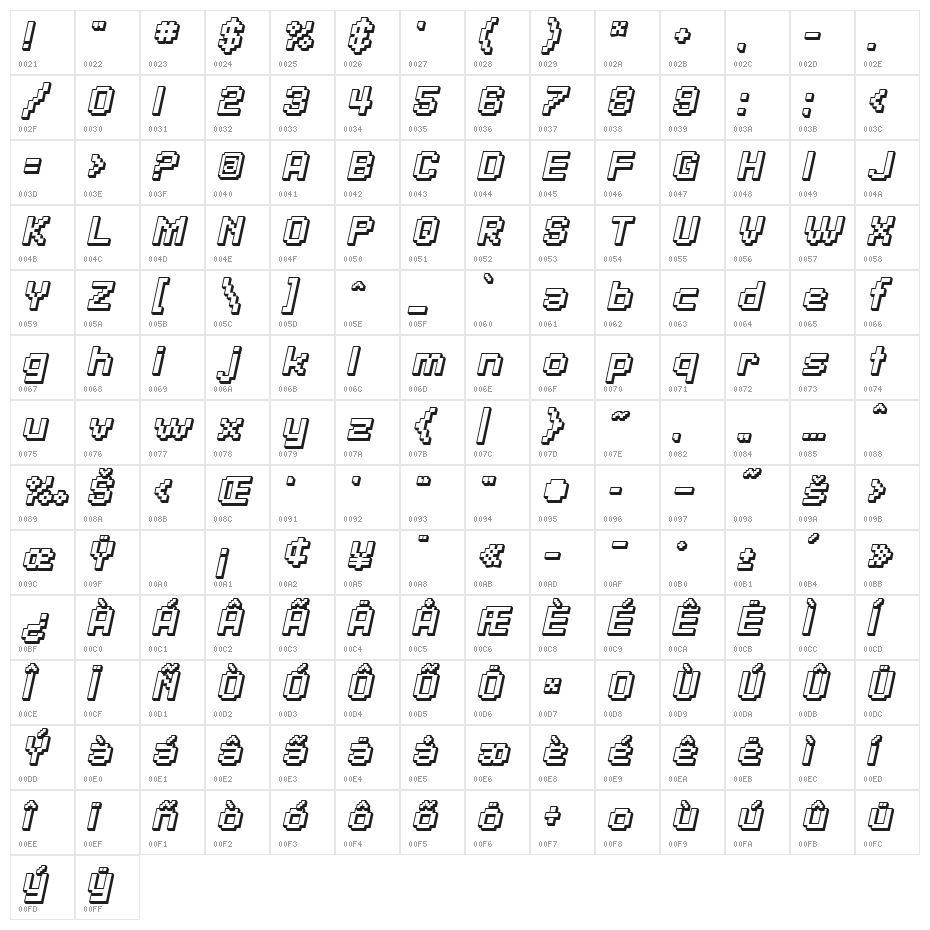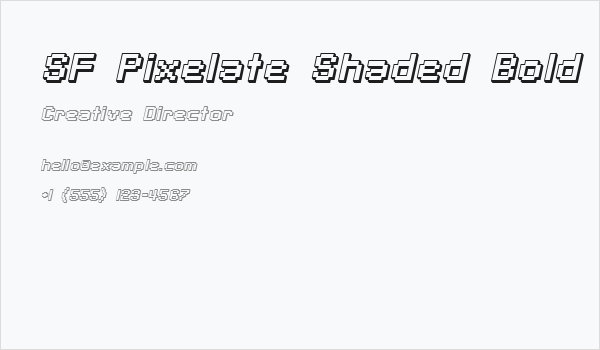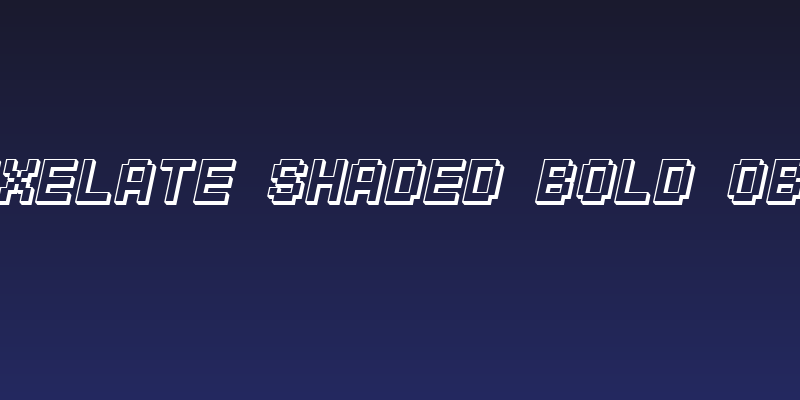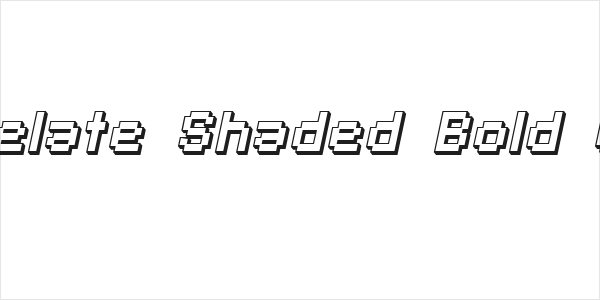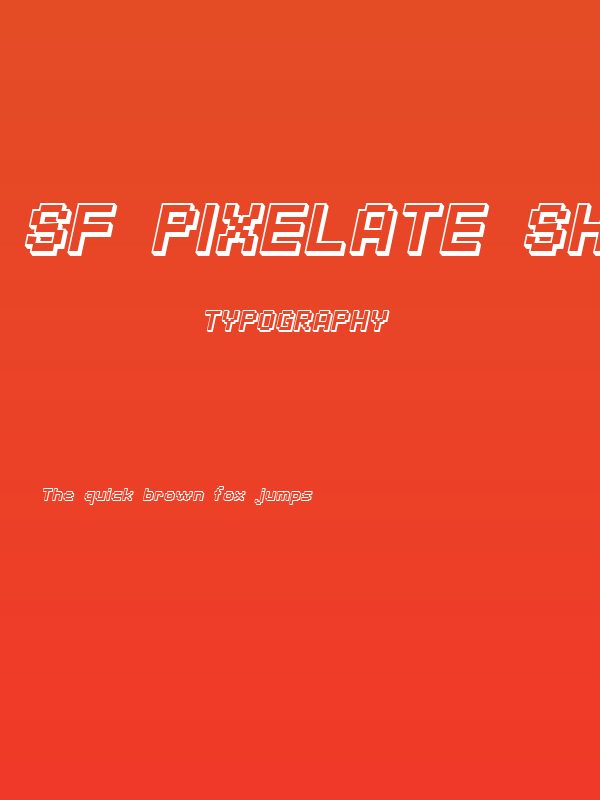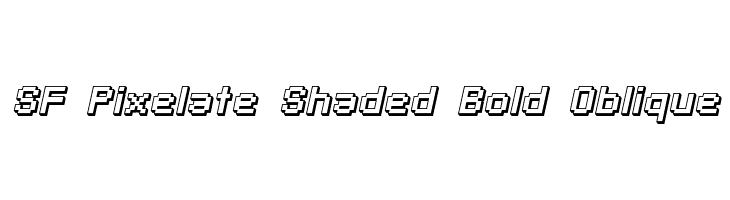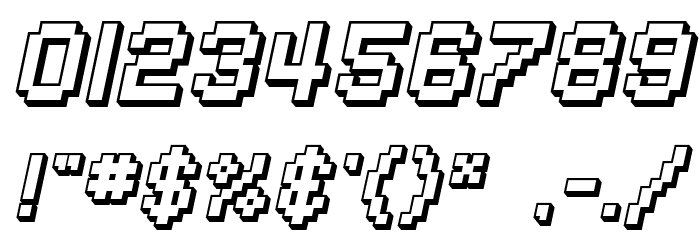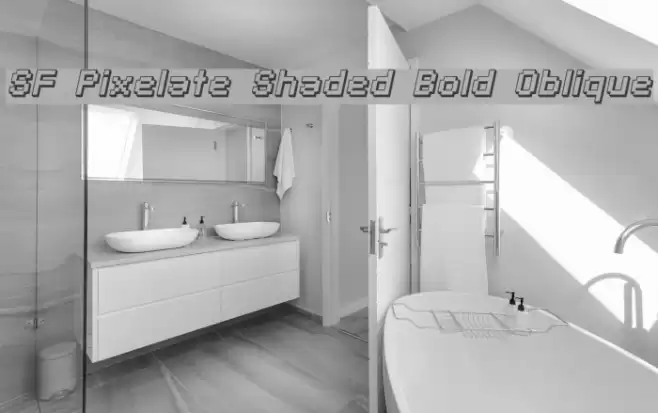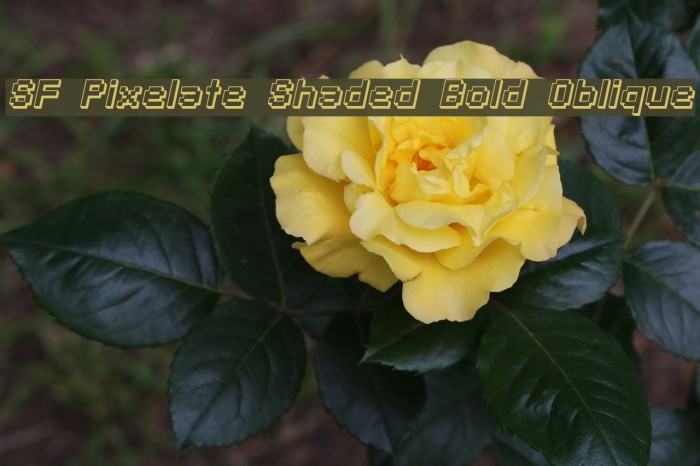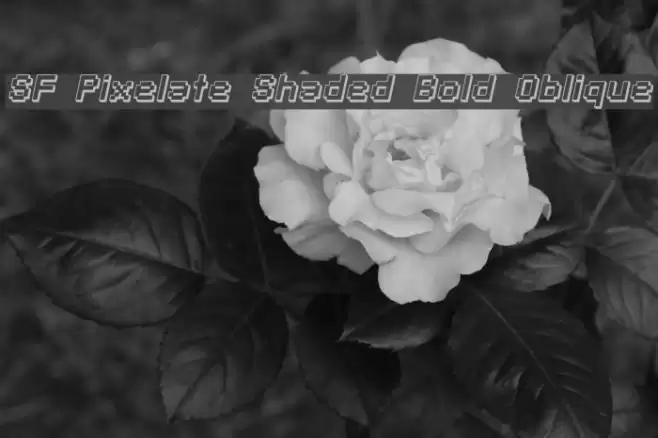
SF Pixelate Shaded Bold Oblique Font
| Name | SF Pixelate Shaded Bold Oblique |
| Gewicht | Bold Oblique |
| Kategorien | Pixel |
| Gesamtstil | Retro, Decorative |
| Anwendungsfall | Logos, Headlines, Posters |
| Vorgeschlagene Projekte | Ideal for video game designs, retro-themed posters, digital art projects, and any creative work requiring a nostalgic, pixelated look. |